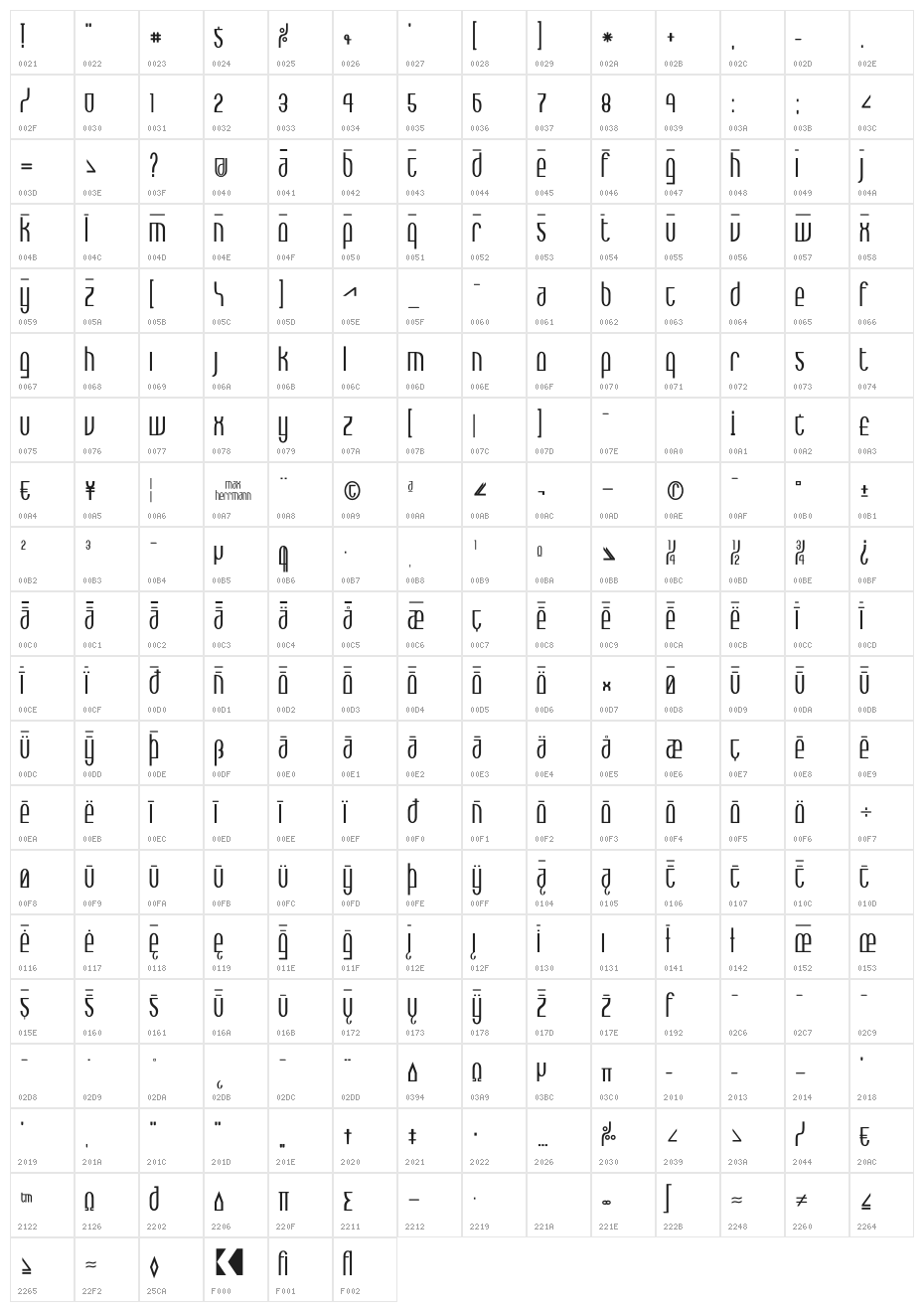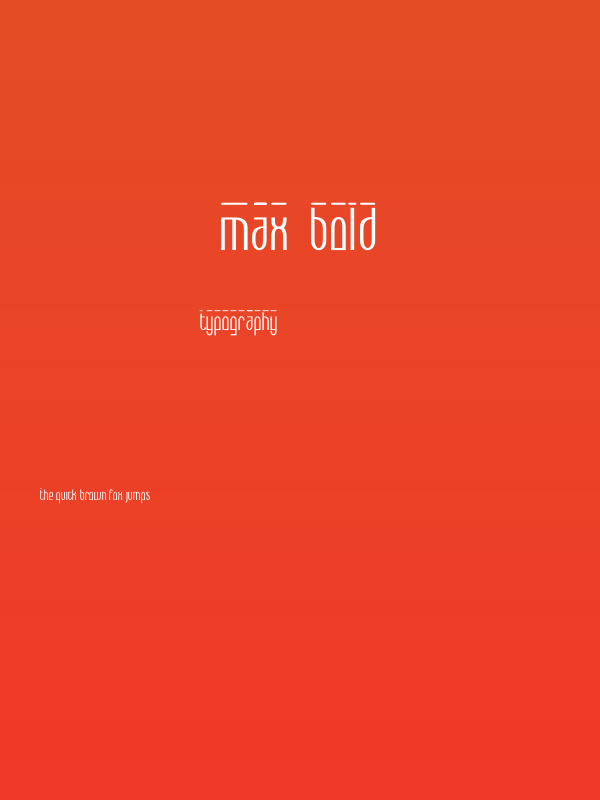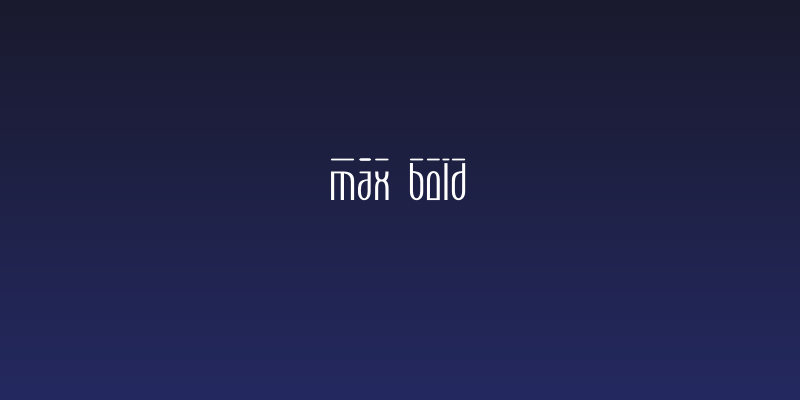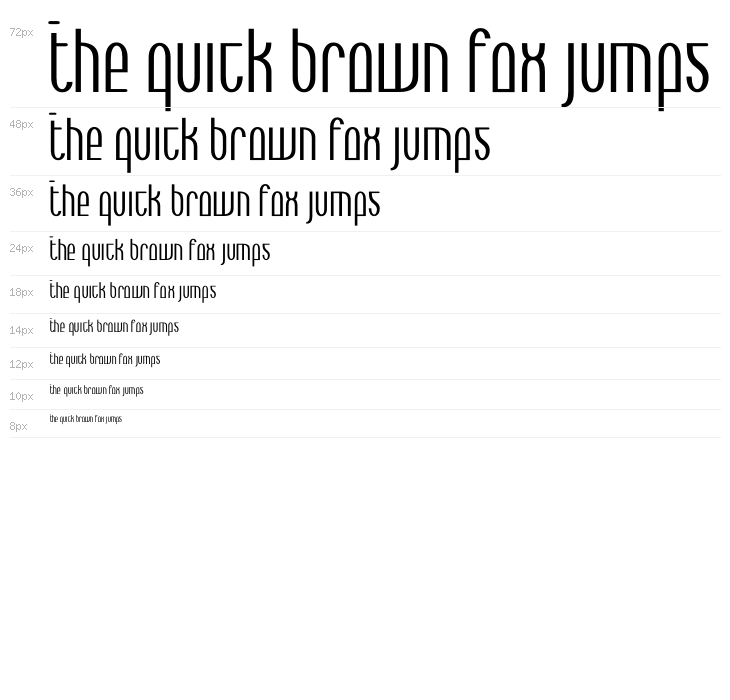
Max Bold Font
| 分类 | Kids |
| 宽度 | Condensed |
| 使用场景 | Headlines, Logos, Digital Interfaces |
| 推荐项目 | Ideal for branding, editorial design, packaging, and digital interfaces where a modern and clean aesthetic is desired. |